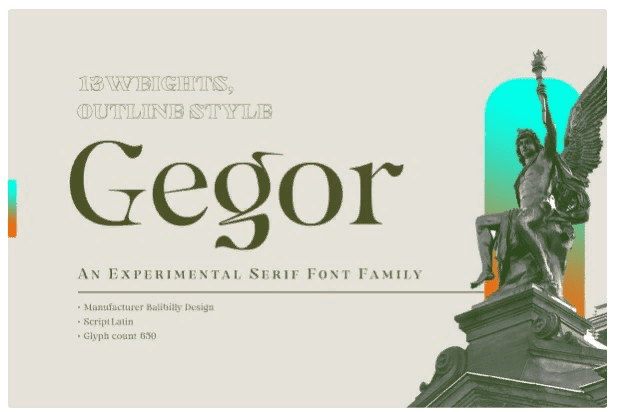
Название: Gegor Font (2021)
Gegor - это свобода нашей руки при создании формы буквы без множества ссылок. Мы стараемся позволить инструменту пера течь и танцевать в соответствии с нашим воображением. Символы этого шрифта заимствованы у буквы "r". Она родилась и влияет друг на друга. Простые формы на плече - слегка заостренные при толстом весе и кривые при тонком весе - оказывают большое влияние на другие буквы. Уникальная форма буквы "r" ведет нас к дальнейшему развитию, чтобы добиться отчетливой гармонии как дисплейного шрифта.
Если вы посмотрите на тизерные изображения и получите представление, то мы уже в строю. Gegor состоит из 14 семейств от тонкого до черного, и 1 контурного стиля в черном весе, оснащенного произвольными лигатурами, формами с учетом регистра, ординатами, малыми прописными буквами и дробями. Поддерживаются несколько языков, включая западноевропейский, центральноевропейский и юго-восточноевропейский.
Gegor идеально подходит для плакатов, логотипов, брендинга, журналов, веб-сайтов и многого другого.
Gegor придаст уникальную вибрацию вашим работам. Ура!!!